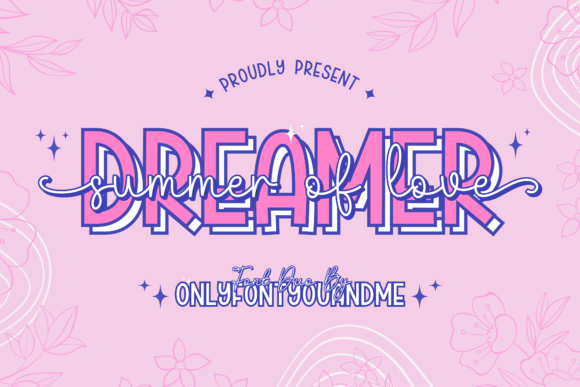
Dreamer Summer of Love
Trouver les bons éléments de conception peut être un défi, mais Dreamer Summer of Love propose une collection exceptionnelle qui rehausse instantanément votre travail.
Conçu avec précision, Dreamer Summer of Love offre des vecteurs nets, une typographie fluide et une licence commerciale pour une tranquillité d'esprit.
Que vous créiez des produits POD (impression à la demande), des invitations de mariage ou des visuels pour les réseaux sociaux, Dreamer Summer of Love est un choix idéal.